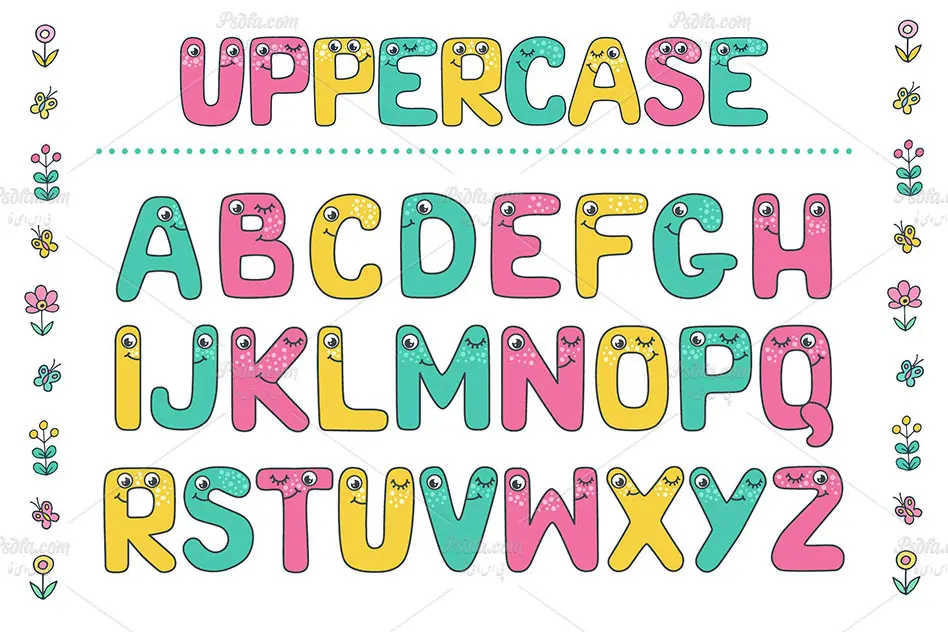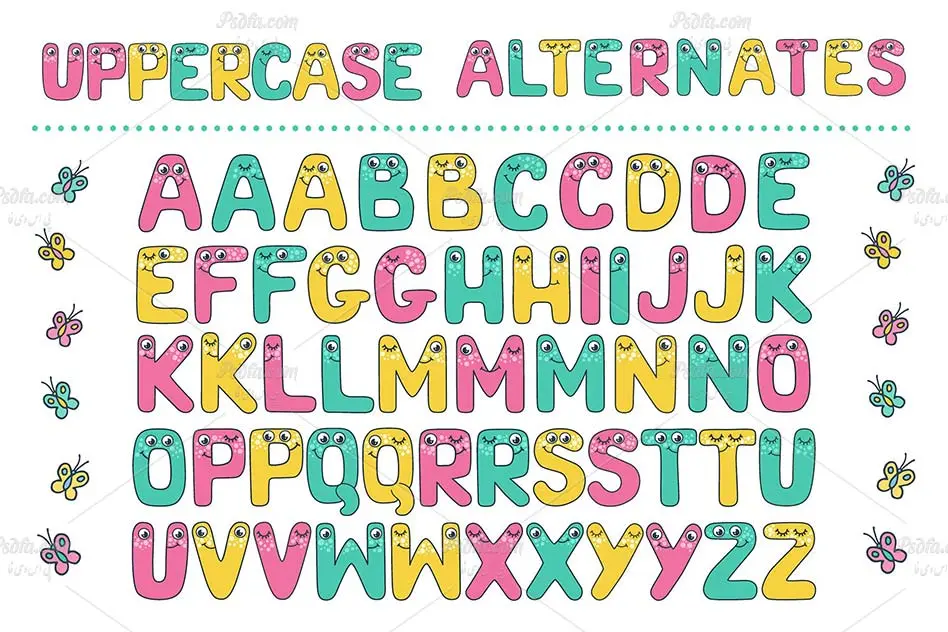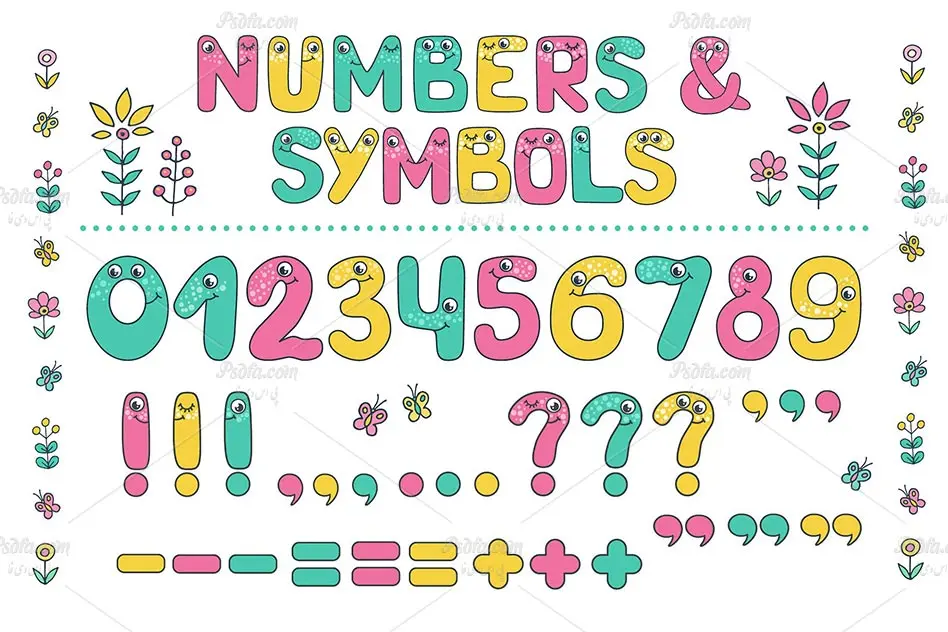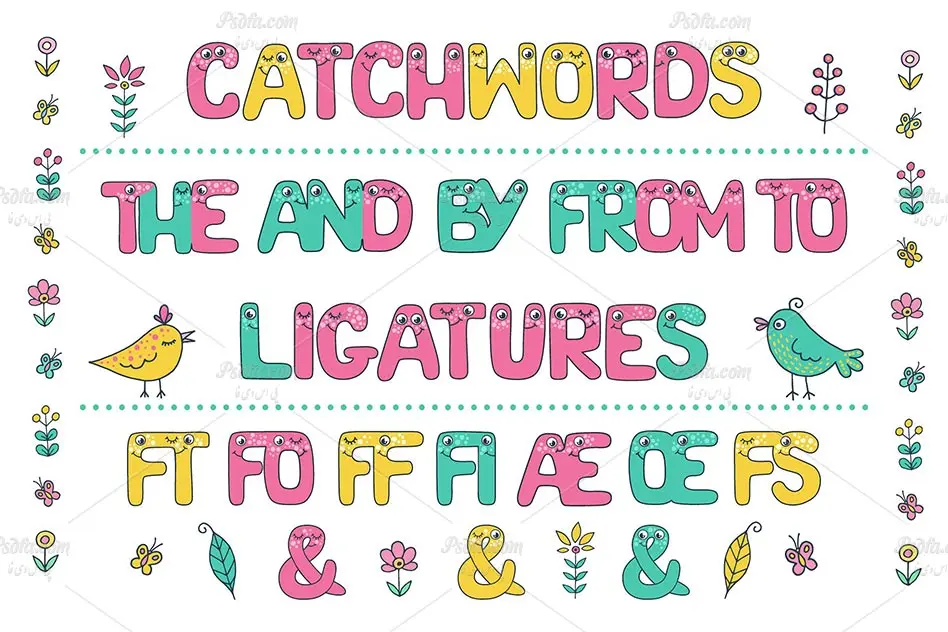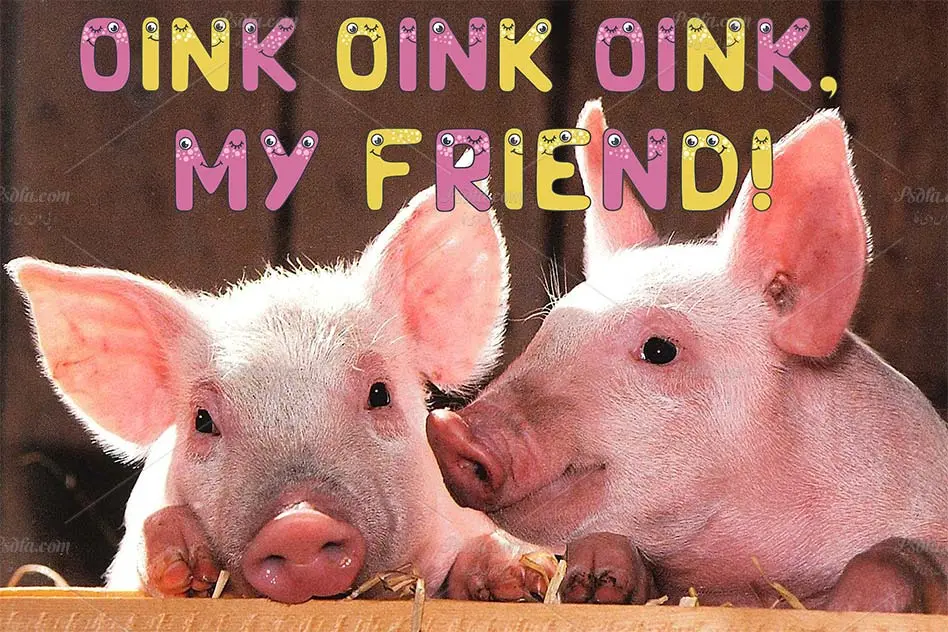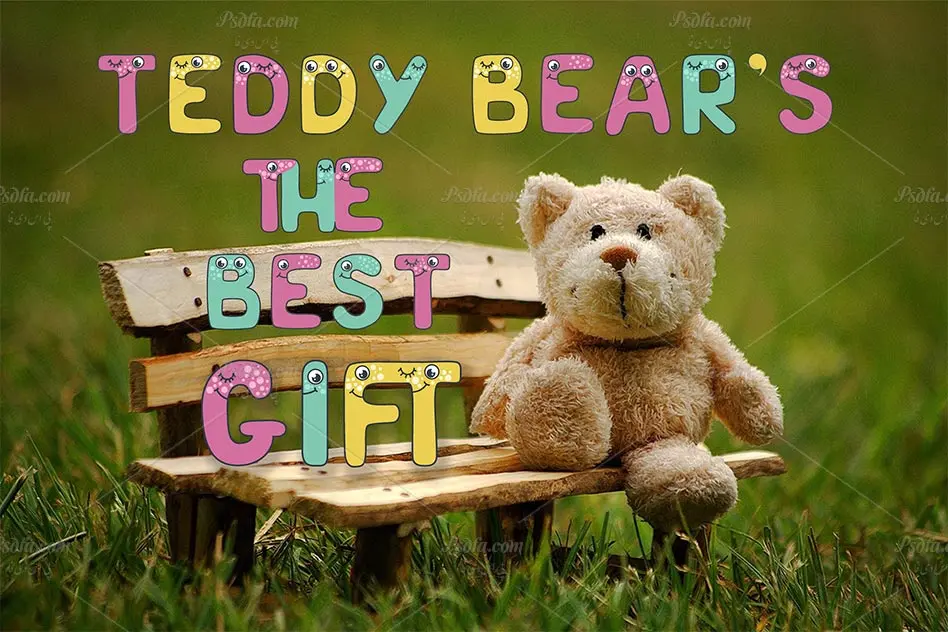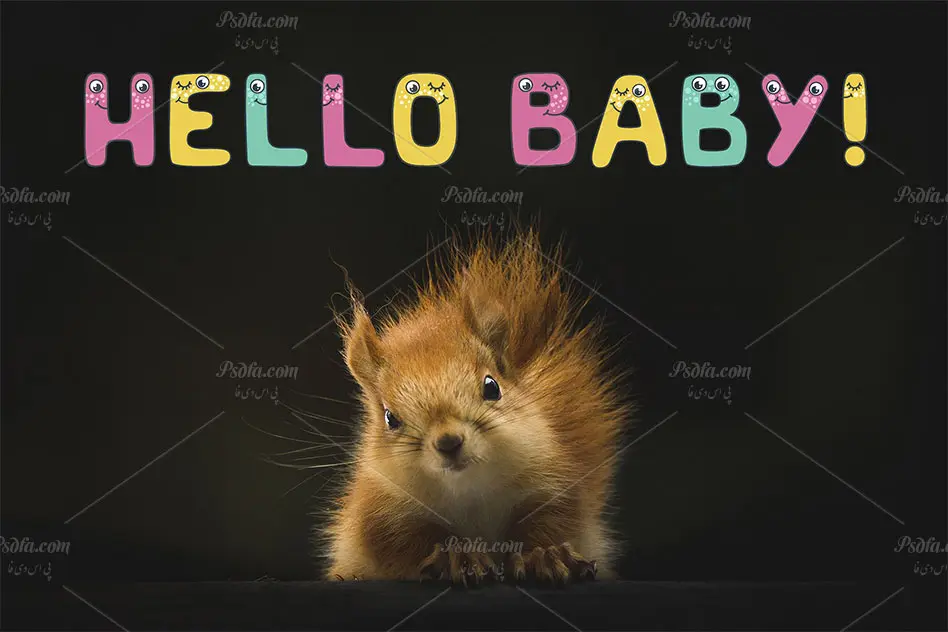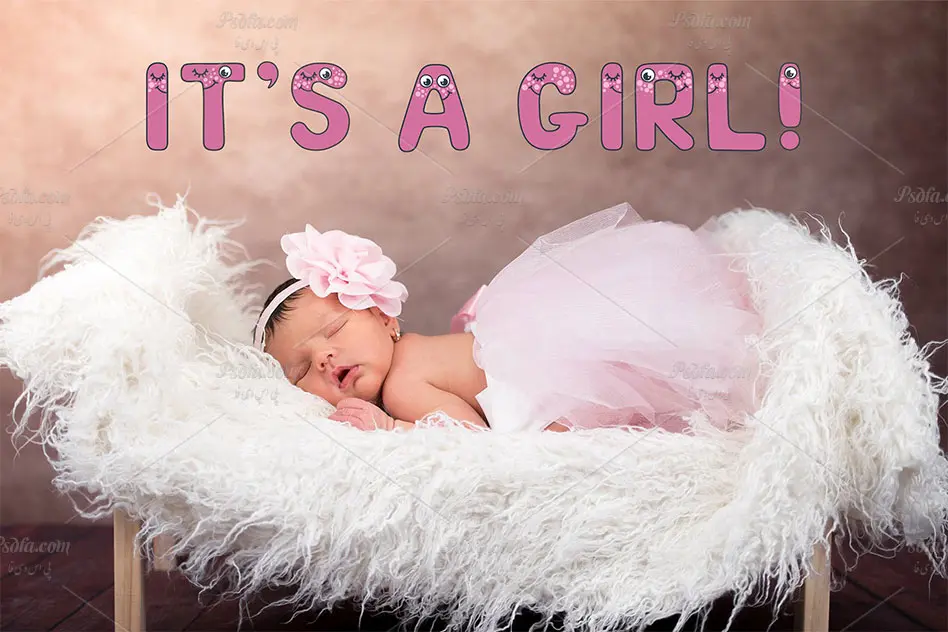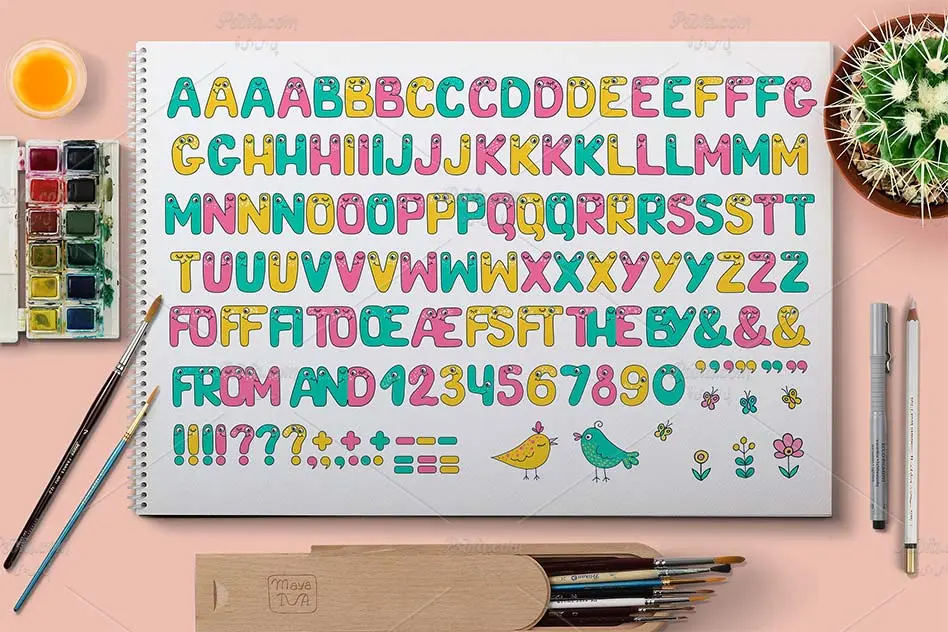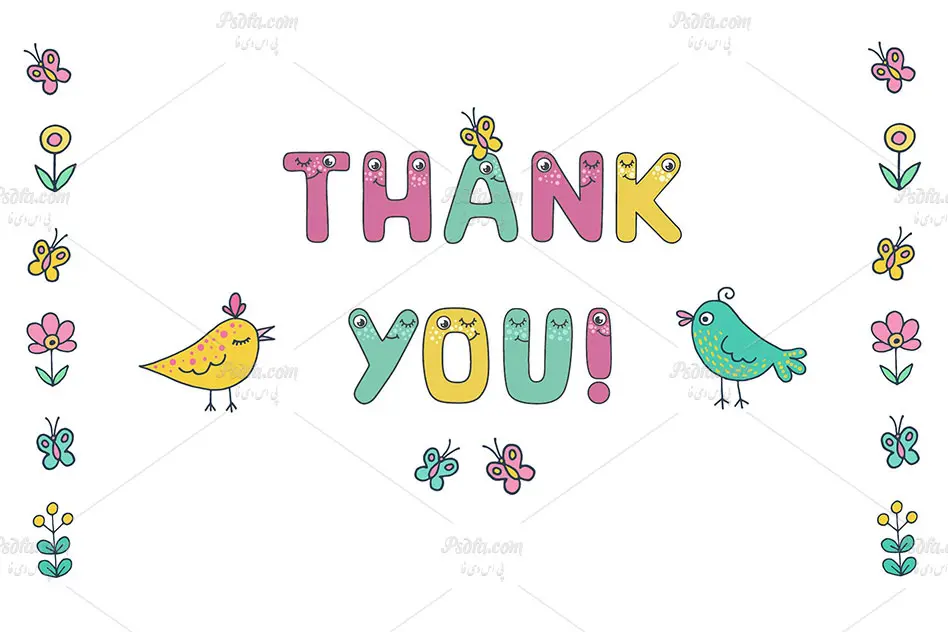
در این مطلب شاهد فونت فانتزی و کودکانه Funny Font مناسب جهت استفاده در طراحی فانتزی و کودکانه می باشید. فونت فانتزی Funny یکی از سری فونت های فوق العاده زیبایی است که می توان آن را در طراحی پروژه های گرافیکی فانتزی و کودکانه مورد استفاده قرار داد. این فونت با فرمت otf در سایت قرار داده شده است که با نصب آن در پوشه فونت های سیستم می توانید از آن در تمام نرم افزارهای گرافیکی و ویرایشگر متن استفاده کنید. البته نکته مهم این است که شما فقط در نرم افزار فتوشاپ CC 2017 و ایلوستریتور CC 2018 به بعد می توانید از نسخه رنگی و خنده دار این فونت استفاده کنید چرا که فونت رنگی یک تکنولوژی جدید است که در نسخه های قبل این نرم افزارها پشتیبانی نشده است. اما اگر شما از نسخه های قدیمی این نرم افزارها استفاده می کنید می توانید از فایل png , eps و یا ai این مجموعه استفاده کنید بدین صورت که باید کاراکترها را در کنار هم بچینید تا یک کلمه بوجود بیاورید. پیشنهاد ما به شما استفاده از نسخه های به روز این نرم افزارهاست. همچنین لازم به ذکر است که این فونت از حروف کوچک پشتیبانی نمی کند و شما فقط می توانید از حروف بزرگ در طراحی استفاده کنید.